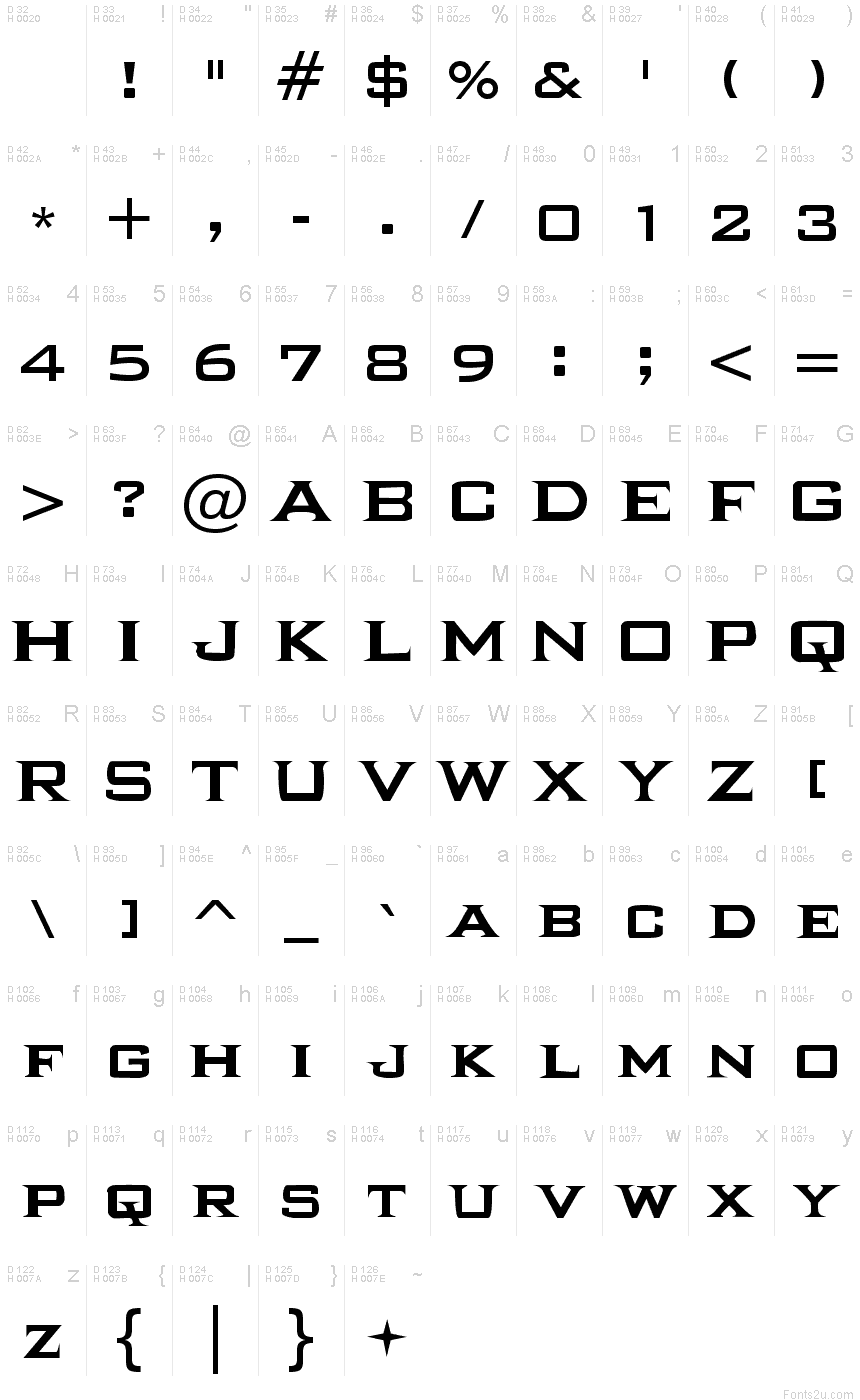
Ikarus od Utopia to darmowy, retro szeryfowy krój pisma, który uderza z siłą i dramatyzmem kinowego tytułu. Szerokie, masywne litery, ostro zarysowane szeryfy i subtelnie ciosany charakter nadają mu śmiałą, niemal filmową obecność. Ciasny i pewny siebie kerning sprawia, że słowa łączą się ze sobą niczym w wykutej inskrypcji, dzięki czemu nagłówki są solidne, wyraziste i nieco niebezpieczne.
Używając Ikarus, możesz stworzyć branding dla zespołu metalowego, salonu gier w stylu retro czy powieści fantasy bez konieczności zmiany fontu. Świetnie sprawdza się również na plakatach, logotypach, tytułach gier, koszulkach czy okładkach płyt, gdzie potrzebujesz ciężkiej, heroicznej energii. Ten darmowy font najlepiej prezentuje się w dużych rozmiarach; połącz go z prostym, geometrycznym bezszeryfowcem w tekście głównym, aby cały ten dramatyzm pozostał w centrum uwagi.